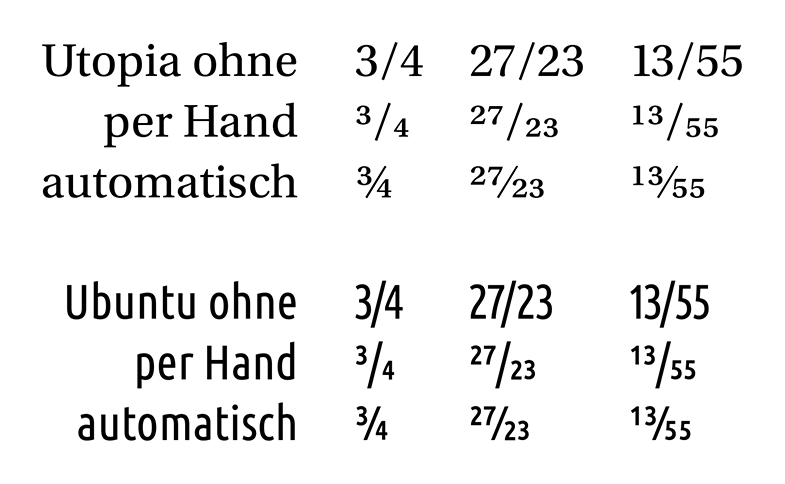
ich möchte ein Schaubild der rationalen Zahlen¹ mit Svg erstellen und für die Beschriftung Bruchzahlen verwenden. Meine vorläufige Wahl der Schrifttype fällt auf „Ubuntu Condensed”; der Schriftgrad ist momentan noch nicht relevant. Das Zielmedium könnte möglicherweise ein Plakat (Din A0, o. ä.) werden. Ich habe bisher alle benötigten Glyphen (hoch- und tiefgestellte Ziffern, Bruchstrich) mittels FontType nach Eps exportiert und auf Svg umgerechnet. Soweit ist auch alles in Ordnung. Wenn ich Brüche (bspw. ½) mit den Standarddickten setzte, gibt es einen feinen Unterschied zur vorgefertigten Glyphe. Der „/” ist minimal (12 Upm) unterschnitten und die „2” hat eine zusätzliche Vorbreite von 6 Upm. Außerdem ist die Grundlinie der „2” um 1 Upm angehoben (ich denke: das kann ich getrost vernachlässigen).
Ich bitte um Eure Meinung bzw. Euren Rat: Sollte ich – aus typographischer Sicht – ein Kerning vornehmen oder ist es tragbar (erträglich) die Standarddickten zu verwenden? Und falls ein Kerning empfehlenswert ist, wonach richtet sich dann der optische Ausgleich?
[¹] Das Schaubild umfasst alle „echten“ Brüche bis zu einem Nenner von bspw. 31, eine „Zeile” für jeden Nenner und an der horizontalen Teilung soll ein „×” mit darunterliegender Beschriftung stehen.
es gibt schriftarten (darunter die ubuntu condensed), die neben dem normalen schrägstrich noch einen bruchstrich (fraction slash) haben, der schräger steht und mit dem opentype-feature ›brüche‹ verknüpft ist. dann musst du die brüche nur eingeben, das feature in einem geeigneten programm zuweisen und fertig. so sieht es aus:
das ergibt vermutlich bei fast allen schriftarten, die dieses feature mitbringen, die optisch ansprechendste darstellung. bei beiden oben gezeigten schriftarten ist das ergebnis in der dritten zeile von der vorgefertigten ¾-bruchzahl für mich nicht zu unterscheiden.
… neben dem normalen schrägstrich noch einen bruchstrich (fraction slash) haben …
Danke für die anschaulichen Beispiele. Den „fraction slash” verwende ich bereits; trotzdem gibt es feine Unterschiede. Aber möglicherweise ist das gar keine Unterschneidung, sondern die Bildschirmoptimierung.
… das feature in einem geeigneten programm zuweisen…
ja, das kann sein, dass das händische eingeben von zählerziffer, bruchstrich und nennerstrich ein anderes ergebnis hat als die anwendung des features ›brüche‹ auf normale ziffern. wie ich schon sagte, lässt sich die darstellung bei dir eigentlich nur dann beurteilen, wenn du uns mal ein beispiel davon zeigst. grundsätzlich würde ich bejahen, dass kerning zwischen bruchziffern und bruchstrich sinnvoll sein kann, aber das ausmaß kann man nur konkret beurteilen.
ich habe übrigens inzwischen noch ein bisschen rumprobiert und bin zu dem ergebnis gekommen, dass die abweichung zwischen dem vorgefertigten bruch und dem selbstgebauten einfach ein ›fehler‹ (oder eine ungenauigkeit) der ubuntu ist. wenn ich (in indesign) manuell die zählerziffern eingebe, kommt ein vom kerning her leicht anderer bruch raus, als wenn ich das brüche-feature auswähle. bei vielen anderen schriftarten ist das auch so, aber nicht bei allen.
Klar! Fehler sollte man nie ausschließen. Ich danke Dir für Deine Anmerkungen; sie haben mich geleitet, dieses Thema zu vertagen. Zunächst mache ich erst einmal das Schaubild fertig und wenn mir dann die Brüche zu löchrig erscheinen, werde ich dann unterschneiden. Bei einem angemessenen Schriftgrad (vielleicht so zwischen 12 und 18 pt) dürfte das wohl noch unter der Rubrik „Feinschliff” fallen; und wenn, dann werde ich jedenfalls stärker unterscheiden, möglicherweise die gesammte Nachbreite der Zählerziffer und Vorbreite der Nennerziffer. Ganz nach dem optischen Eindruck. Danke.
gern geschehen! das war auch mein eindruck, dass sich bei einer normalen lesegröße höchstens dann anpassungen anbieten würden, wenn du ganz am ende zu viel zeit hast. notwendig ist es sicher nicht, wenn die abweichungen überall so sind wie in dem von dir gezeigten beispiel. vielleicht hast du ja lust, irgendwann mal das schaubild zu zeigen. dann gibt hier bestimmt noch mal gerne jemand seinen senf dazu. viel erfolg!
Ich hab’ ein wenig aufgeräumt und weitergemacht. Wie man bei (13/25)
http://abacus.acamat.de/rational/Test03.svg
deutlich sehen kann, komm’ ich um ein kerning sowieso nicht ‘rum. Und dabei ist der fraction slash noch das kleinste Übel. Es sind bei der Ubuntu übrigens keine Kerning-Paare für diese Ziffern hinterlegt. Das wird ein Spaß! :-(
Hat jemand einen Tipp für einen effizienten Arbeitsplan? Erst einmal mit Standarddickte setzen und danach Feinschliff oder vorher alle denkbaren Zifferkombinationen durchkauen? Schließlich habe ich hier 496 Brüche geplant… und um die zwangsläufig-folgerichtige Frage gleich vorweg zu beantworten: Ja, ich schreib’ mir kleines Setzprogramm dafür. :-)
Warum setzt Du das Schaubild mitsamt den Brüchen nicht gleich in einem DTP- oder Vektorgraphik-Programm? Dann kannst Du Dir Umwege mit Formatumwandlungen sparen und die in der Schrift hinterlegten Unterschneidungsanweisungen werden genutzt. Du kannst zum Beispiel das kostenlose Programm Inkscape verwenden. (Aus Inkscape kannst Du das fertige Schaubild dann u. a. als PDF- oder SVG-Datei ausgeben lassen.) Mit TeX geht das Ganze sicher auch und läßt sich dann je nach Aufbau Deines Schaubildes sogar weitgehend automatisieren.
Übrigens: Für diesen Font sind – zumindest beim Afm-Export von TypeTool – keine kerning pairs für die hoch- und tiefgestellten Ziffern hinterlegt. Das müsste ich dann sowieso selbst vornehmen.